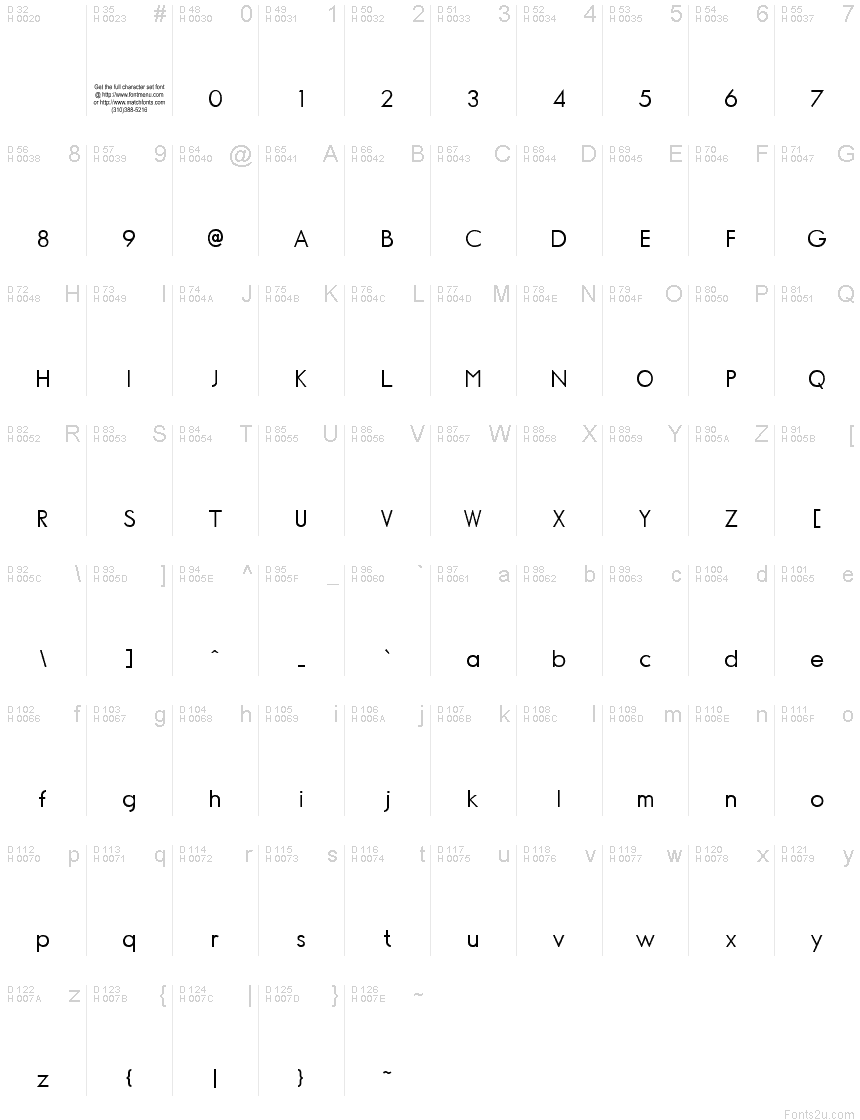
Normographe to darmowy krój bezszeryfowy o zaokrąglonych, geometrycznych literach i płynnym, równym rytmie kreślenia. Kształty są minimalistyczne i precyzyjne, z szerokimi, kolistymi oczkami i prostą konstrukcją, co nadaje całej rodzinie wyrazisty, techniczny charakter przypominający rysunek techniczny.
Normographe świetnie sprawdza się w logotypach, akcentach redakcyjnych, etykietach opakowań, tytułach plakatów i oznakowaniach, wszędzie tam, gdzie potrzebny jest stonowany krój bezszeryfowy. Ten bezpłatny font pasuje również do systemów identyfikacji wizualnej i krótkich nagłówków, ponieważ zaokrąglone formy zapewniają przejrzystość tekstu, dodając mu jednocześnie unikalnego, technicznego klimatu.